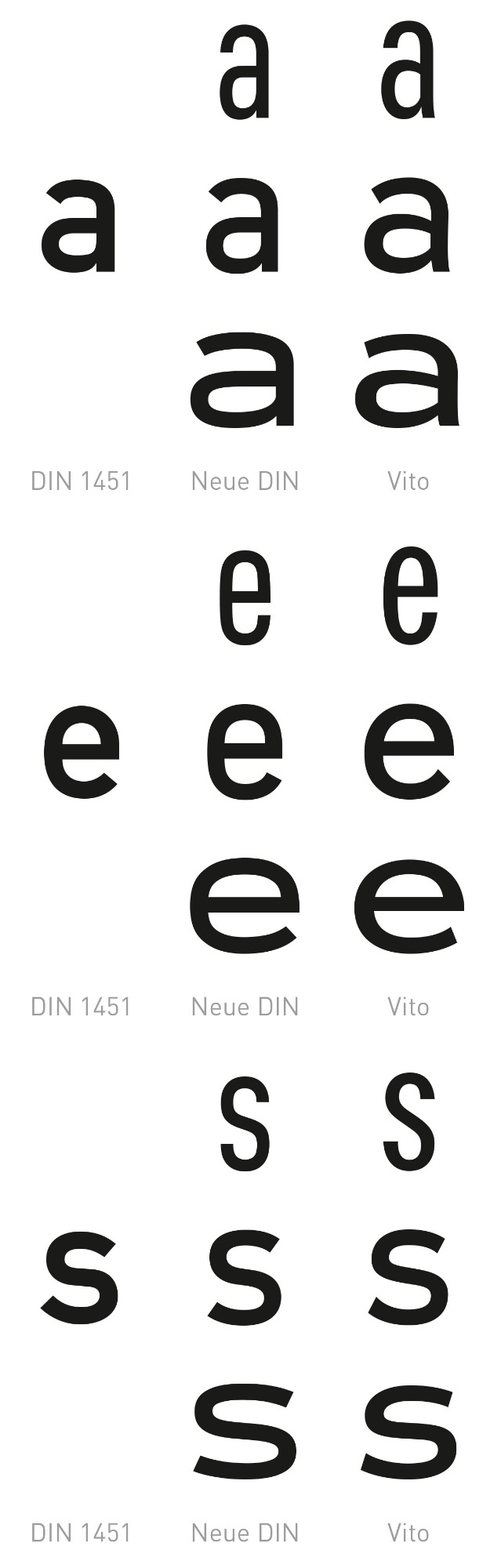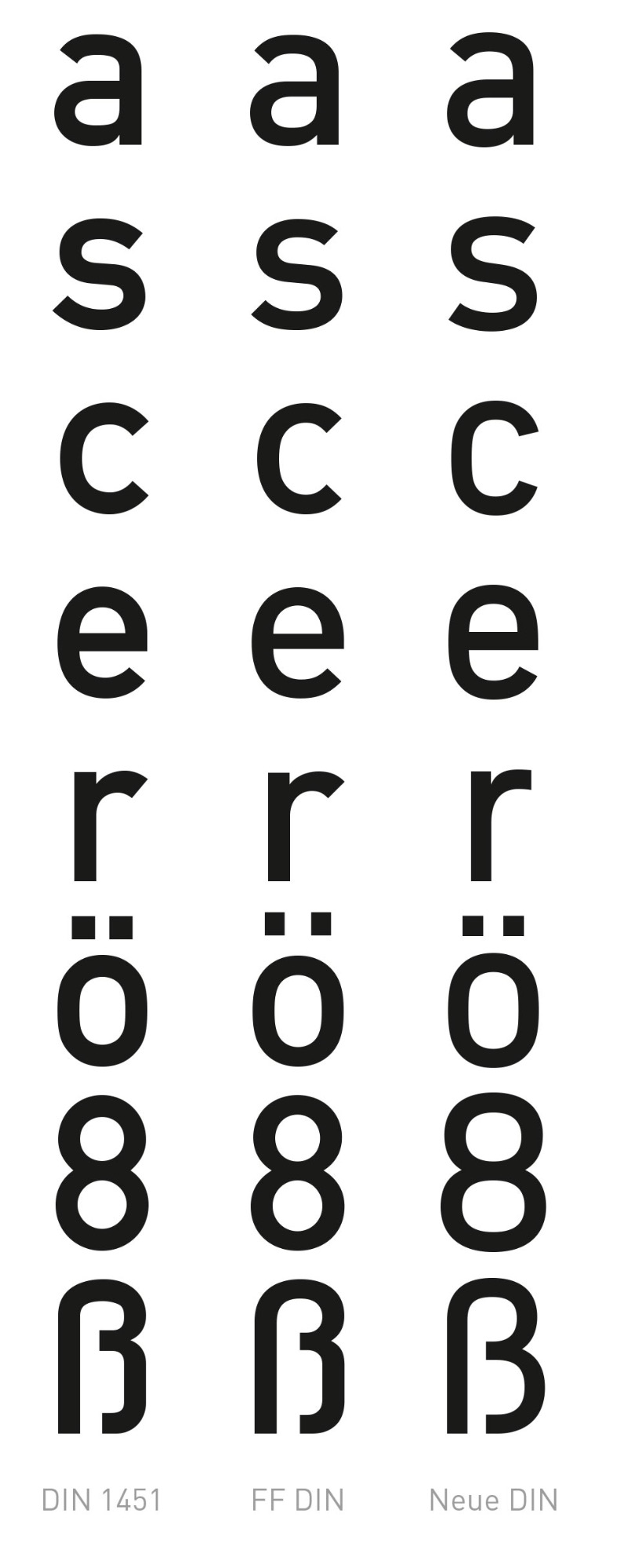
was ist das nur immer mir diesen A …?
Das passiert, wenn man sich beim Export der fertigen Fontdatei darauf verläßt, daß das Programm alle separaten Bausteine verschmilzt.
wobei das mit DIN nix mehr zu tun hat, der name ist wohl eher marketing.
Wieso hat das mit DIN nichts mehr zu tun? Die extrem schmalen und breiten Schnitte sind natürlich gewöhnungsbedürftig aber das Gerüst ist trotzdem DIN. Marketing ist aber natürlich auch mit dabei.
Hast du dir mal den Text zur Neuen DIN durchgelesen?
Bei dem ging mir bei allem Marketing irgendwie das Herz auf. 🙊
Ich habe mich aber auch gefragt, ob man die schmalen Schnitte wirklich so hätte schließen und die Weiten dermaßen öffnen müssen. Auf der anderen Seite ist man da wohl einfach nur den alten Entwürfen gefolgt und hat sie in beide Richtungen konsequent weiter extrapoliert. 🤷🏼‍♂️
eben weil diese XXSchnitte mit der der ursprünglichen form der DIN nix mehr zu tun haben, die sind ja ganz nett aber ich würde es nicht DIN nennen.
Hmmm, wenn ich mir die Gestaltungsschwankungen in der DIN-Historie so ansehe, wäre ich da nicht so streng. 😉
Hätte man die DIN vor 100 Jahren so ausgebaut hätte das Ergebnis durchaus so aussehen können. Es war damals ja durchaus üblich, dass bei verschiedenen Schnitte unterschiedliche Gestaltungsprinzipien zum Einsatz kamen. Eben weil nicht interpoliert sondern neu gezeichnet wurde. Ich denke da z.B. an die Trade Gothic …:-?
sehe ich ähnlich, wobei ich die weiten noch nichtmal geöffnet empfinde, eher im gegenteil. vergleicht man die formen von XXcondensed bis xxwide sehe ich noch nicht mal das gleiche gerüst. da wurden in meinen augen 2 bzw. 3 verschiedene fonts clever gemorpht.
nicht falsch verstehen, in sich sind das schöne schriften bzw. eine schöne familie aber für mich hat es nix mit DIN zu tun, dann kann ich auch univers, akzidenz, tusker, kapra, zeppelin, vito, plak ...  et cetera pp. als DIN bezeichnen.
es gibt nicht DIE DIN, abgesegen von der FF DIN. 😍 aber wenn man sich die geschichte der DIN anschaut ist da alles dabei was irgendwie konstruiert, schnell erfassbar und ggf. einfach zu nachzuzeichnen ist. das sehe ich in der neuen DIN (vorallem meine ich die X bis XX schnitte) nicht, mir fehlt der konstruierte ansatz.
hätte man das überhaupt gemacht?
in der interstate, tasse bzw. steilen futura, binder style oder iwan reschniew sehe ich  mehr DIN als in den XX schnitten der neuen DIN
Ich schau mir gerade die DIN 1451 an und kann dem beim besten Willen nicht zustimmen. Konstruiert ist für mich die PDU aber bei der DIN gibt es so viele Details die eben nicht konstruiert sind oder zumindest nicht so wirken.
Ich verstehe, dass sich die XX-Schnitte nicht direkt wie eine klassische DIN anfühlen. Aber wäre das überhaupt möglich gewesen und ist das 2023 nötig? Und weil du die Vito erwähnt hast hier mal ein Vergleich zwischen DIN 1451, Neue DIN und Vito. Wenn die Vito mehr DIN ist als die Neue DIN dann komme ich ehrlich gesagt nicht mehr mit ...
Aber was mir noch aufgestoßen ist und wir vielleicht ähnlich empfinden ist, dass ungleichmäßig steile Gerüst (vergleiche a und e), was allerdings der DIN 1451 auch ähnlich ist. Im Beschreibungstext* wird das „Kurvige“ zwar als bewusste Entscheidung beschrieben, aber warum dann nicht auch beim a etc. oder eben überall konsequent gerade (so wie etwa bei der Config, was dann auch eher konstruiert wirkt)?
Trotzdem keimte in uns der Wunsch nach einer eleganten Note, Andreas Frohloff hatte die zündende Idee: „Alle senkrechten Rundungen, etwa die Seiten des o, d oder g, sind rund, haben keine Geraden und schwingen leicht.“ Die Bögen fallen zwar nicht ins Auge, geben der Schrift aber den gewünschten Hauch Eleganz. Mit diesen subtilen organischen Formen und einem ausbalanciertem Spacing sehen wir den sachlichen Charakter gewahrt und sind überzeugt, dennoch ein eigenständiges und zukunftsfähiges Design erschaffen zu haben.
Aber deren Interpretationen sind viel origineller als DIN Next oder Neue DIN.
Aber genau das »originelle« passt doch überhaupt nicht zur DIN. Für meine Begriffe soll die »Neue DIN« gar nicht origineller sein sondern Bereiche (sehr schmal und sehr weit) abdecken die es bisher nicht gab. Das als Idee ist dann wiederum originell.
Eine Neuauflage ist immer eine heikle Sache und natürlich ergeben sich mitunter extrem ähnliche Formen und andere Formen unterscheiden sich sehr deutlich.